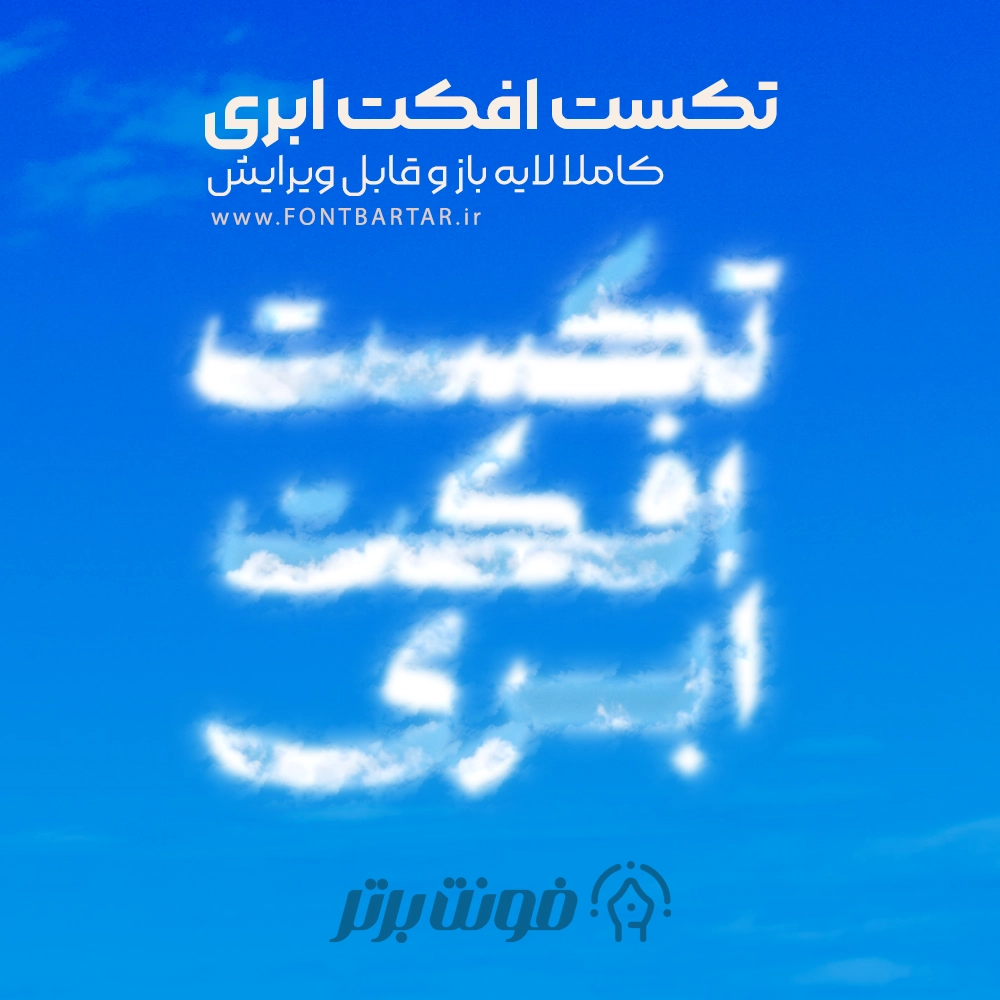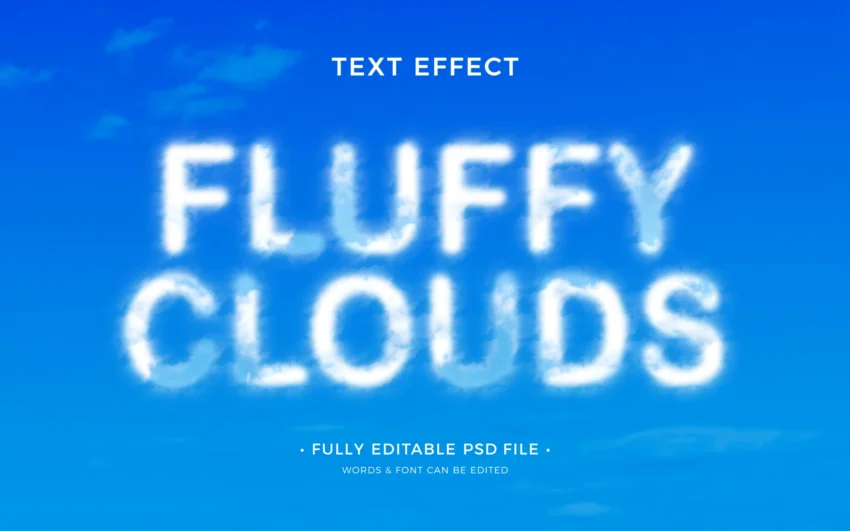
تکست افکت ابری لایه باز | متن ابری خاص و قابل ویرایش
تکست افکت فتوشاپ ابری یکی از جذابترین و خلاقانهترین سبکهای طراحی متن است که حس سبکی، آرامش و خلاقیت را به مخاطب منتقل میکند. تصویری که مشاهده میکنید نمونهای از یک تکست افکت ابری لایه باز است که بهصورت حرفهای طراحی شده و امکان ویرایش کامل متن را در فتوشاپ فراهم میکند. تکست افکت فارسی متنی انتخابی عالی برای طراحانی است که به دنبال خلق طرحهایی متفاوت، چشمنواز و ترند هستند.
تکست افکت ابری چیست؟
تکست افکت ابری نوعی افکت متن گرافیکی است که نوشتهها را به شکل ابرهای واقعی یا نقاشیشده نمایش میدهد. دانلود افکت تکست فتوشاپ معمولاً با رنگهای آبی، سفید و آسمانی طراحی میشود و برای القای حس خیالپردازی، آزادی و آرامش بسیار کاربردی است.
ویژگیهای تکست استایل ابری لایه باز
تکست استایل فتوشاپ کاملاً استاندارد و حرفهای آماده شده است:
- طراحی مدرن و ترند
- مناسب پروژههای فارسی
کاربردهای متن ابری در طراحی